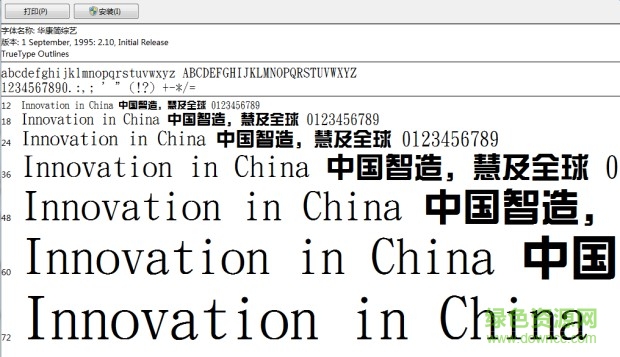
dfzongyi bd 80 win gb
dfzongyi bd 80 win gb(华康简综艺)是一款粗壮雄峻的华康字体,字形浑厚醒目,笔画饱满晶莹,看上去厚实有力,想要这款字体的朋友快来绿色资源网下载吧!
综艺体介绍
综艺体是一种常用的美术字体,特点是笔划更粗,尽量将空间充满。同时为了美观,对拐弯处的处理较为圆润。方正、微软等各大字库都有开发,常被用于广告、报刊等的标题。